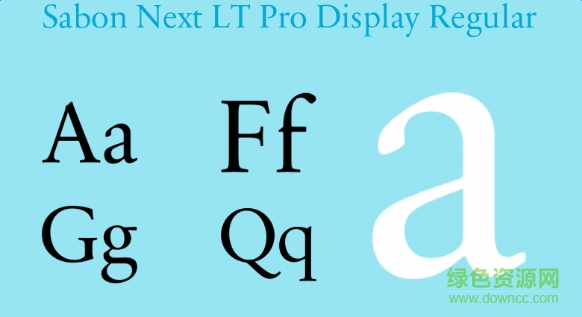
sabon next 字體
sabon next字體是一款應(yīng)用廣泛的英文字體,筆畫纖細(xì)優(yōu)雅,字型端正,網(wǎng)頁制作、廣告設(shè)計(jì)、ppt文案等領(lǐng)域都可以使用這款字體,喜歡的朋友歡迎在綠色資源網(wǎng)下載!
英文字體分類
西方國家字母體系分為兩類:serif以及sans serif。
serif,意思是在字的筆畫開始、結(jié)束的地方有額外的裝飾,而且筆畫的粗細(xì)會(huì)有所不同。
sans serif,無襯線字體,沒有這些額外的裝飾,而且筆畫的粗細(xì)差不多。